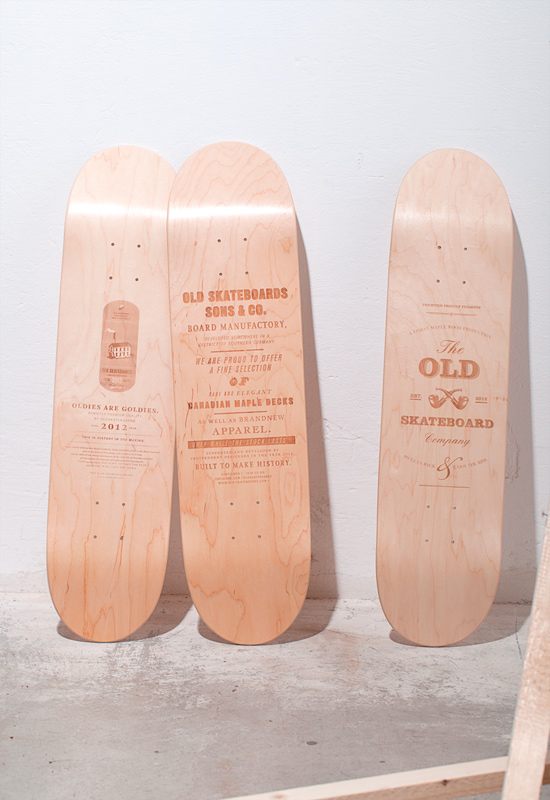
Old Skateboards – Typografie auf dem Brett
Fundstück: Wunderschöne Skateboards mit noch viel außergewöhnlicher Typo. Thumbs up!
Pressetext: Altes Europa, 2012. Die Bretter, die die Welt bedeuten haben keinen Vorhang, sondern vier Rollen. Jedenfalls für Old Skateboards. Die Marke für anspruchsvolle Rollbretter in nostalgischem Design interpretiert skateboarden auf neue Art und Weise – in nostalgischem Look.
Mit den ersten holzgravierten Sammlerstücken beginnt die Geschichte auf facebook.com/oldskateboards und in ausgewählten Galerien, in der die streng limitierten Editionen vorgestellt werden. Old Skateboards ist eine Marke von Liebhabern für Liebhaber – ein Kollektiv aus Designern, Künstlern und Illustratoren, die ihre Leidenschaft fürs Skateboarden und für Design mit einer einzigartigen Bildsprache auf die Straße bringen.
Hochwertige Bretter aus Ahorn-Holz werden mit neuester Technik veredelt. So ist eine limitierte Kollektion von Sammlerstücken entstanden, die bald in verschienen Galerien zu sehen sein wird – designed and branded in Old Europe.